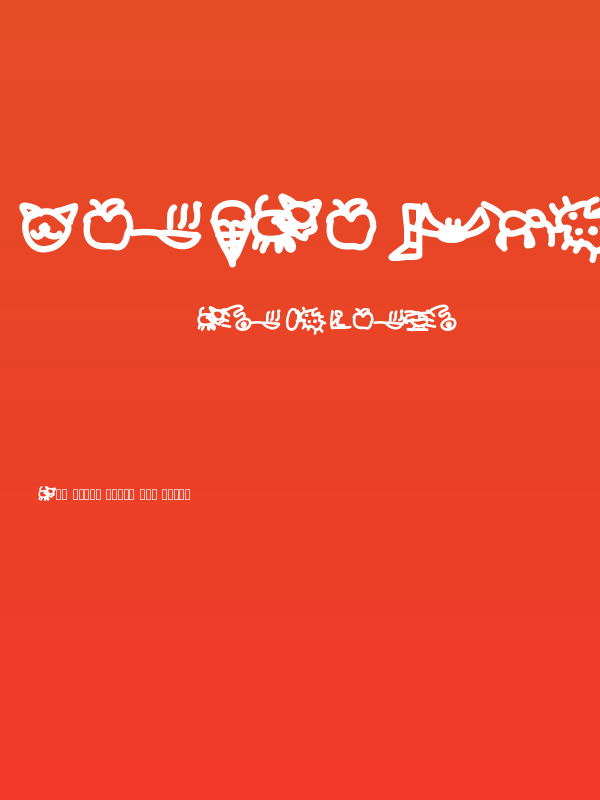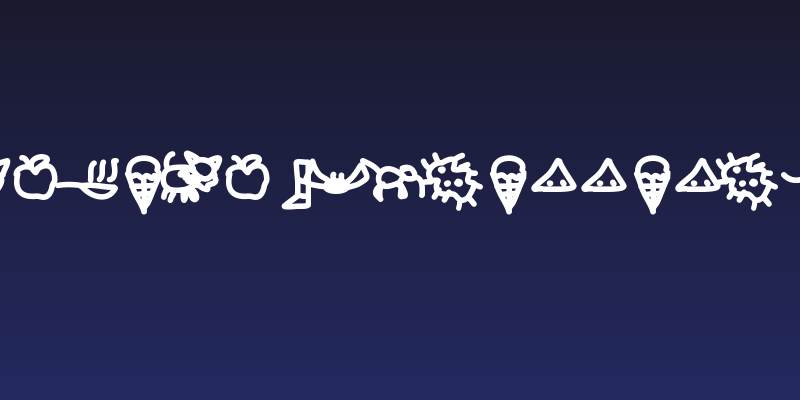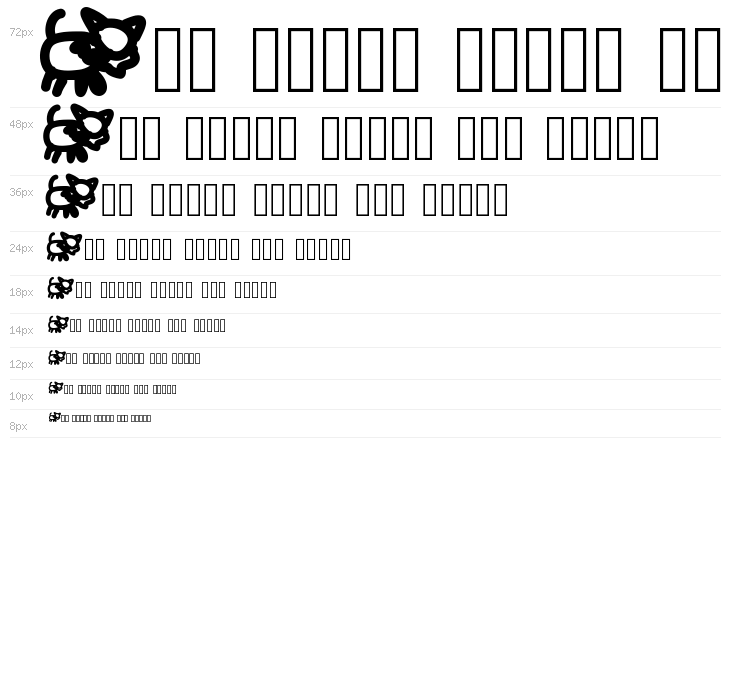
capitalbeginnings Font
| Gesamtstil | Decorative, Whimsical, Playful |
| Anwendungsfall | Logos, Headlines, Posters, Children's materials |
| Vorgeschlagene Projekte | Children's books, party invitations, playful branding, educational materials, creative posters, and art projects. |